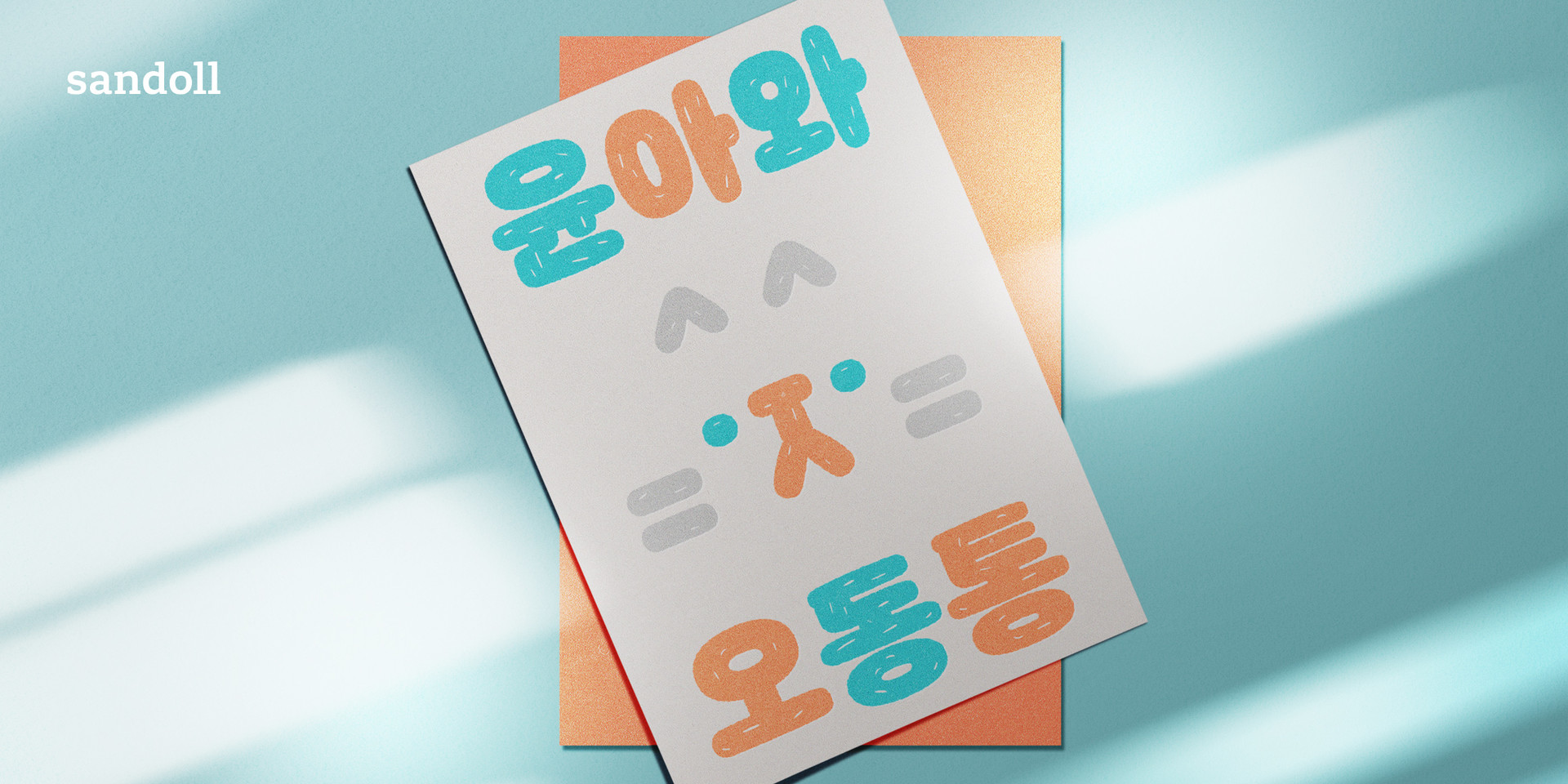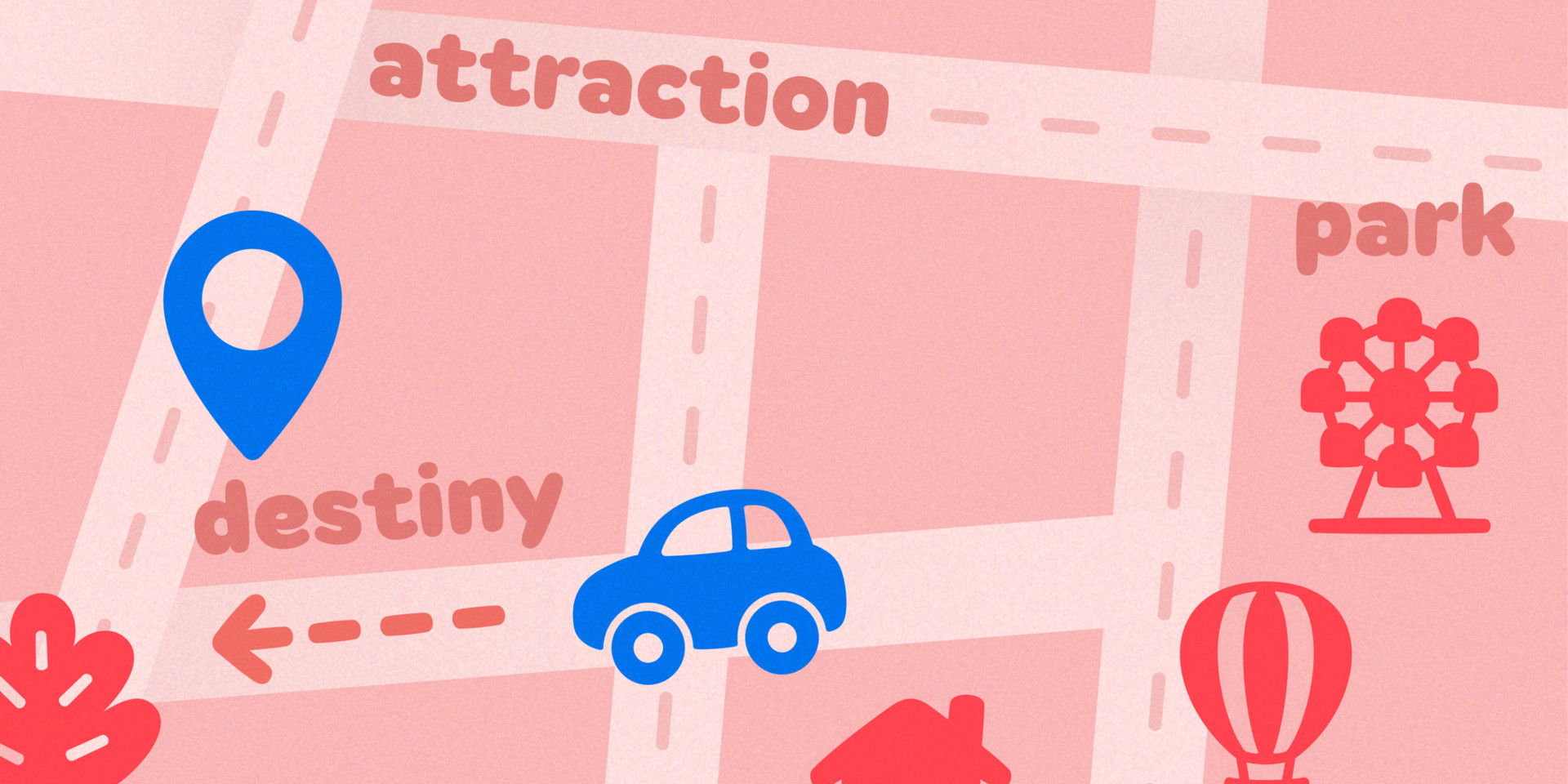
Sandoll 오동통
산돌 오동통은 두꺼운 매직으로 쓴 글씨를 연상시키는 동그랗고 귀여운 인상의 폰트입니다.
‘ㅁ’, ‘ㅅ’, ‘ㄷ’ 등에서 손글씨의 획을 느낄 수 있으며, 꺾임이나 획의 모양이 둥글둥글한 느낌을 줍니다.
또한 스타일별로 웨이트를 구분해 기본 텍스처인 Basic과 반짝이는 텍스처의 Bling, 털실 같은 느낌의 Fluffy를 다양한 곳에 재미있게 사용할 수 있습니다.
두꺼운 웨이트와 둥근 획을 가지고 있기 때문에 일러스트나 만화책의 제목같이 친근하고 캐주얼한 용도에 사용하기에 좋습니다.